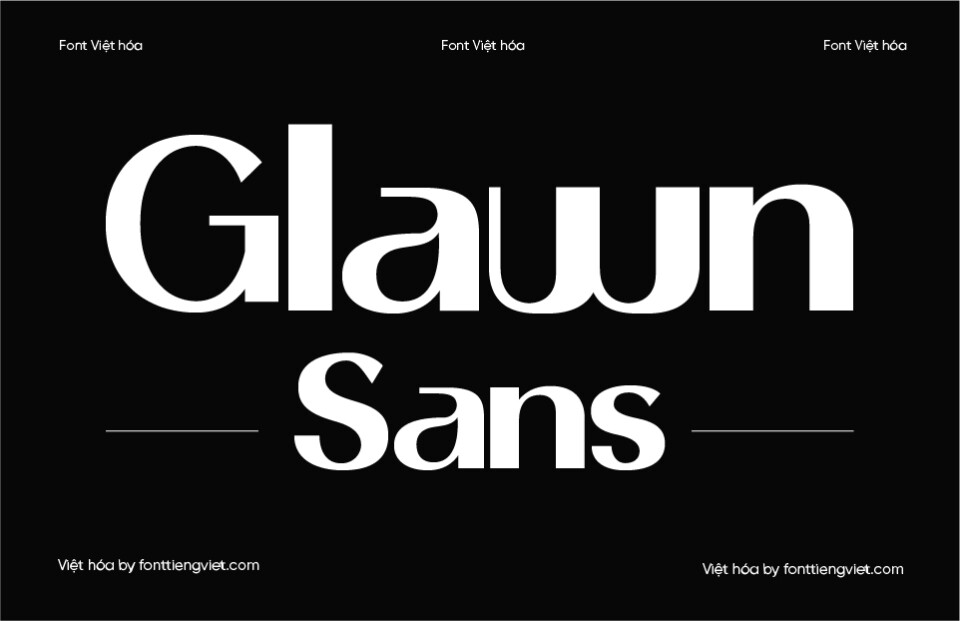
Font Việt hóa 1FTV VIP Glawn Sans
Giới thiệu về bộ Font Việt hóa 1FTV VIP Glawn Sans độc đáo
Trong thế giới thiết kế đồ họa hiện đại, việc tìm kiếm một bộ Font Miễn Phí chất lượng cao luôn là ưu tiên hàng đầu của các designer. Font Việt hóa 1FTV VIP Glawn Sans nổi lên như một hiện tượng nhờ sự kết hợp hoàn hảo giữa nét hiện đại và sự tinh tế trong từng đường cong. Đây là bộ phông chữ thuộc dòng Sans-serif (không chân) nhưng lại mang trong mình hơi thở của sự sang trọng, thường được sử dụng trong các dự án đòi hỏi tính thẩm mỹ cao và sự chuyên nghiệp tuyệt đối. Khi được đội ngũ 1FTV tiến hành Việt hóa tỉ mỉ, bộ font này đã khắc phục hoàn toàn các lỗi hiển thị dấu tiếng Việt, giúp người dùng tại Việt Nam tự do sáng tạo mà không lo về vấn đề kỹ thuật.
Tại sao Font Việt hóa 1FTV VIP Glawn Sans lại được ưa chuộng?
Điểm đặc biệt nhất của Font Việt hóa 1FTV VIP Glawn Sans chính là cấu trúc hình học cân đối. Các ký tự được thiết kế với độ dày vừa phải, tạo cảm giác thanh thoát nhưng vẫn đảm bảo tính dễ đọc trên cả thiết bị di động và ấn phẩm in ấn. Đối với các bạn học sinh hay thầy cô giáo, bộ font này cực kỳ phù hợp để làm slide bài giảng hoặc báo cáo vì nó mang lại sự gọn gàng và hiện đại. Không chỉ dừng lại ở đó, Glawn Sans còn sở hữu các biến thể đa dạng, giúp người dùng linh hoạt trong việc nhấn mạnh nội dung quan trọng.
Ứng dụng thực tế của Font Việt hóa 1FTV VIP Glawn Sans trong đời sống
Khả năng ứng dụng của Font Việt hóa 1FTV VIP Glawn Sans là vô cùng rộng lớn. Trong lĩnh vực thương hiệu, nó thường xuất hiện trên các logo của các nhãn hàng thời trang cao cấp hoặc mỹ phẩm. Đối với cộng đồng yêu thích decor, bộ font này là lựa chọn số một để thiết kế thiệp mời, menu quán cà phê hay các poster quảng cáo sự kiện trường học. Nhờ bộ dấu được căn chỉnh chuẩn xác theo quy tắc tiếng Việt, văn bản của bạn sẽ trở nên chuyên nghiệp hơn bao giờ hết, tránh được tình trạng dấu bị lệch hoặc quá to so với chữ cái gốc.
Lưu ý khi sử dụng Font Việt hóa 1FTV VIP Glawn Sans
Dù là một phông chữ đẹp, nhưng khi sử dụng Font Việt hóa 1FTV VIP Glawn Sans, bạn cần chú ý đến khoảng cách giữa các dòng (line-spacing) để tối ưu hóa trải nghiệm thị giác. Việc kết hợp Glawn Sans với các font Serif (có chân) cổ điển cũng là một gợi ý tuyệt vời để tạo nên sự tương phản thú vị cho bản thiết kế. Hãy luôn đảm bảo rằng màu sắc của font chữ nổi bật trên nền ảnh để thông điệp được truyền tải rõ ràng nhất.
Kết luận về giá trị của Font Việt hóa 1FTV VIP Glawn Sans